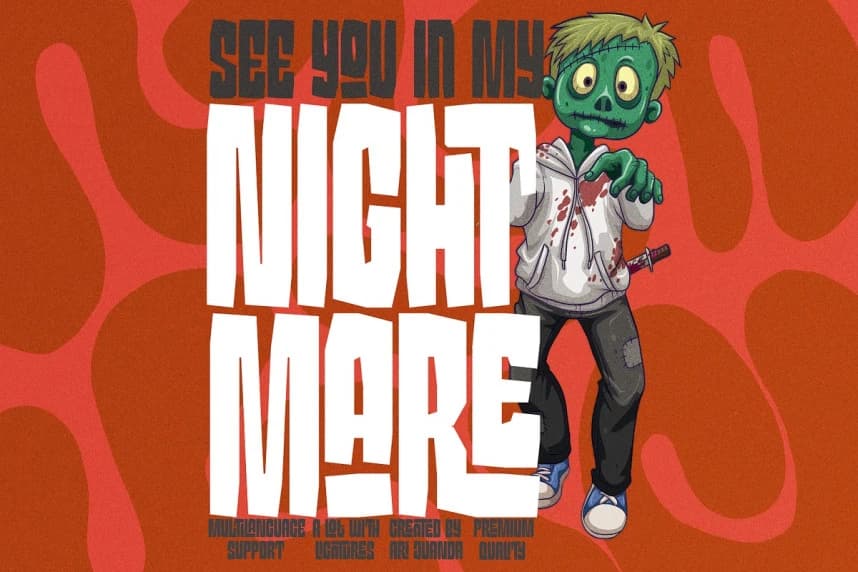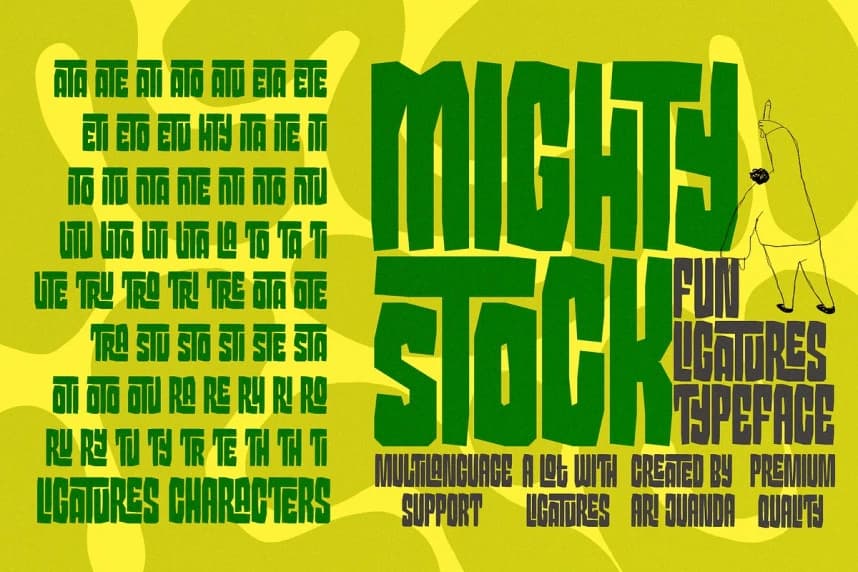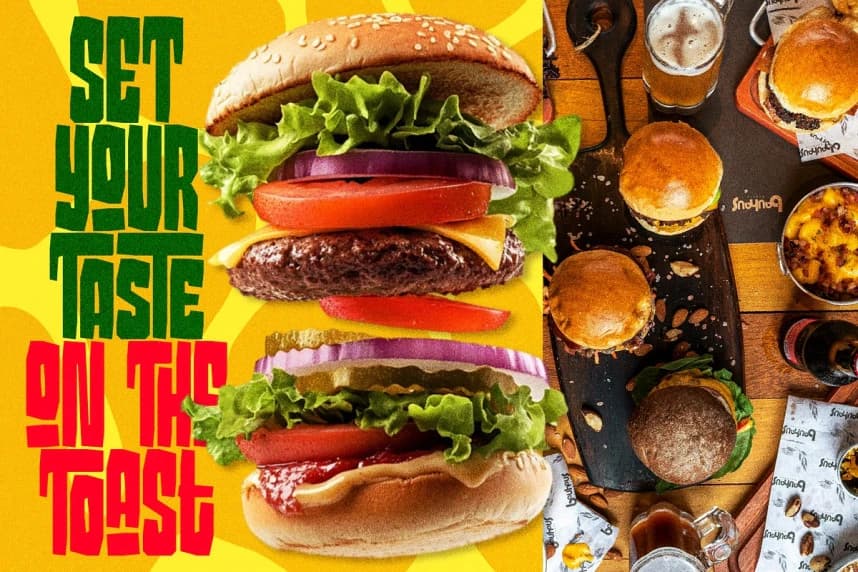
Classic Tomato Font
Classic Tomato Font güçlü ve ifadeli bir gösteri yazı tipi olarak tasarlanmıştır ve güçlü, çarpıcı bir görsel etki sunmayı amaçlar. Kalın, sağlam harf biçimleri ve hafifçe oyunbaz oranlarıyla bu yazı tipi, öne çıkmayı ve anında dikkat çekmeyi hedefleyen tasarımlar için mükemmeldir.
Classic Tomato Font, güçlü ve ifade dolu bir gösterişli yazı tipidir ve güçlü, göz alıcı bir görsel etki yaratmayı amaçlar. Kalın, sağlam harf biçimlerine ve hafifçe oyunbaz oranlara sahip olan bu yazı tipi, öne çıkmayı ve hemen dikkat çekmeyi hedefleyen tasarımlar için mükemmeldir